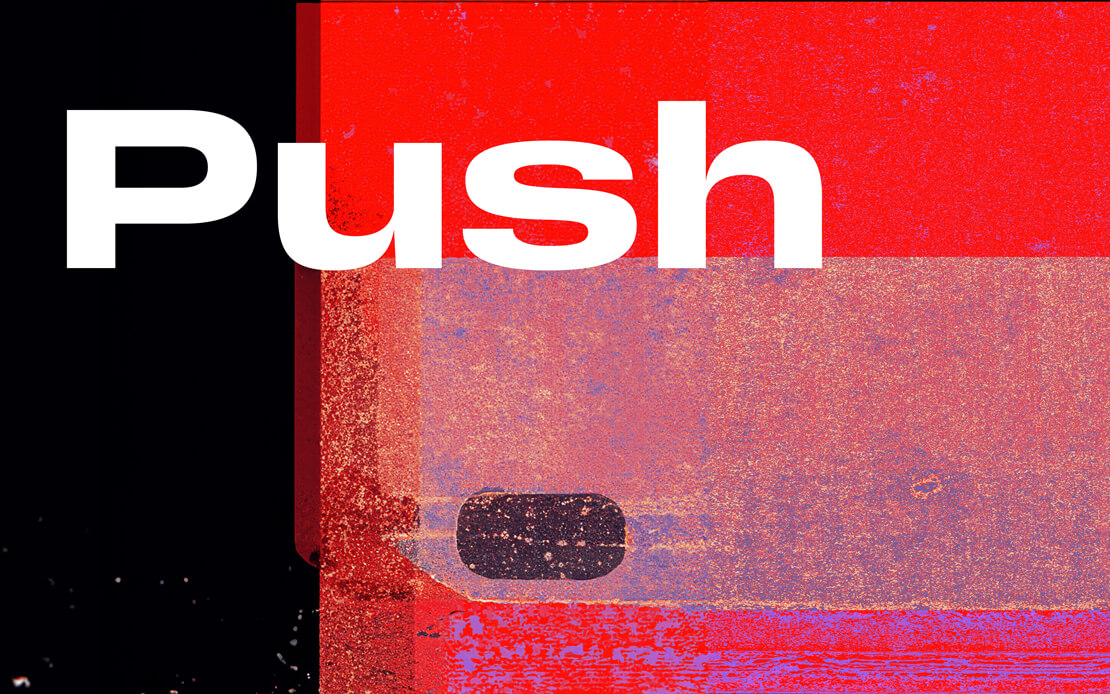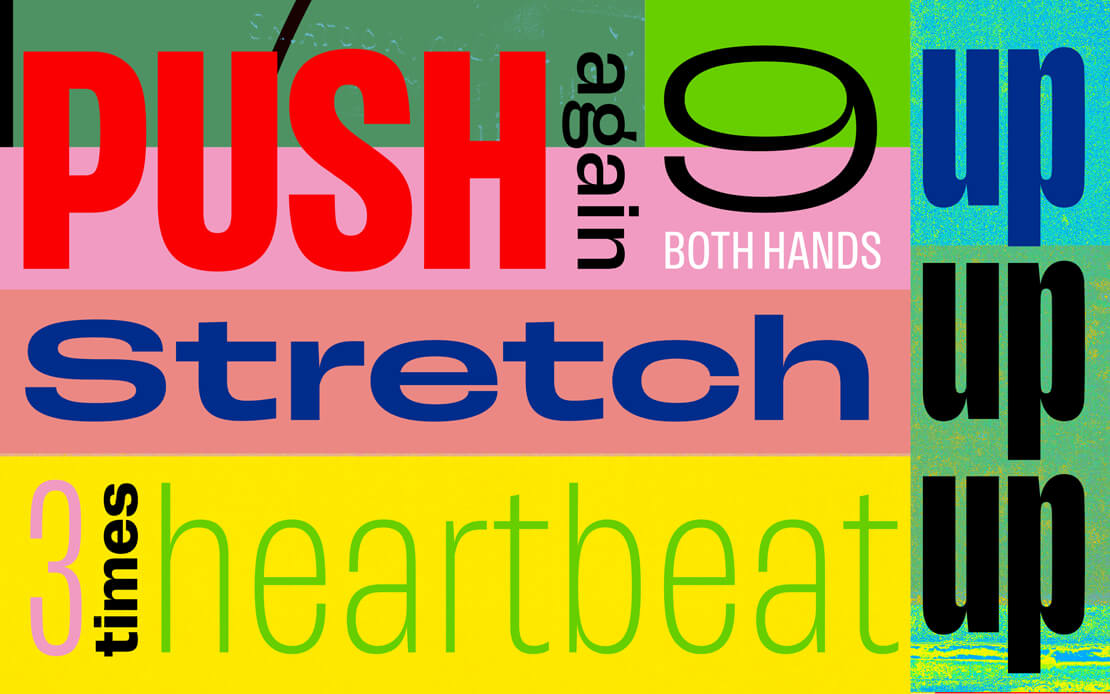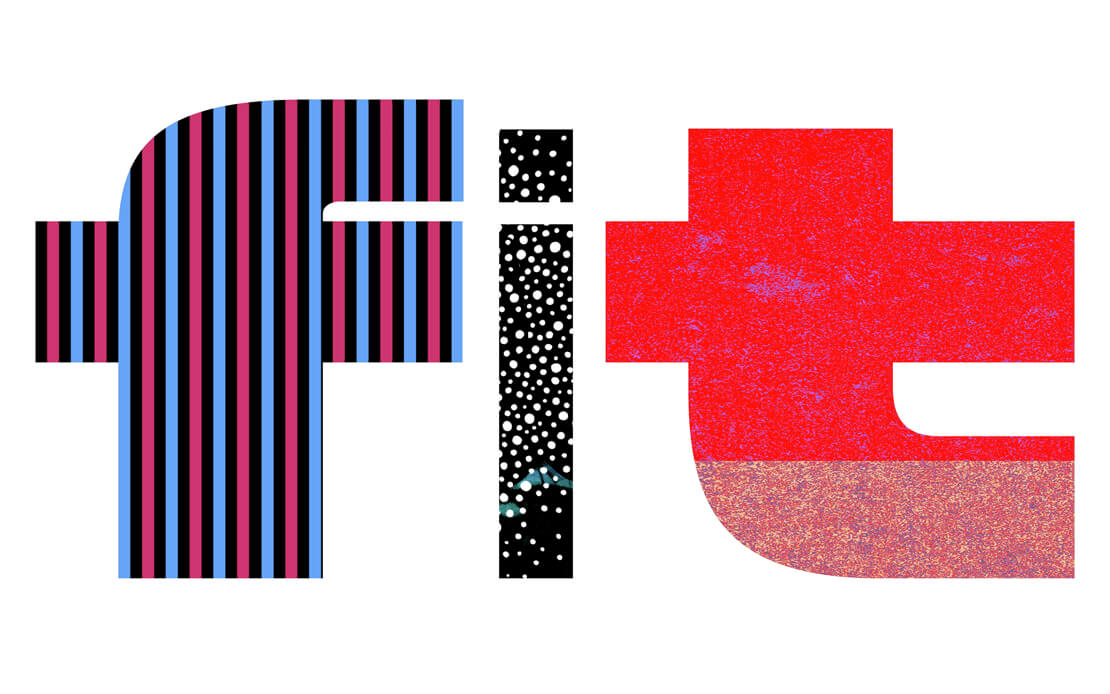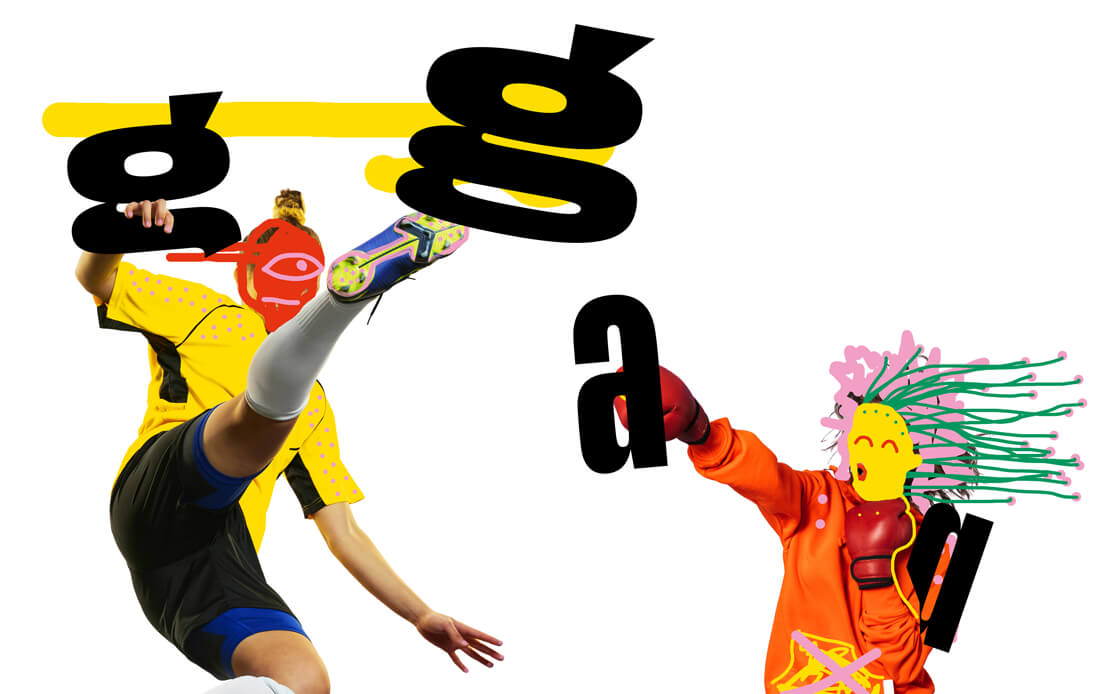
Neue Schriftfamilie »Push« bei Fontwerk erschienen
Fontwerk hat die von Christine Gertsch gestaltete Schriftfamilie »Push« veröffentlicht. Sie enthält sieben Weiten in acht Stärken und vereint dabei Eigenschaften aus amerikanischen Gothics und europäischen Grotesken.
Das Schriftbild von der Schriftfamilie Push bringt Elemente aus den ersten 100 Jahren der serifenlosen Schriften zusammen. Zum Beispiel ist das schmale, fette »G« ohne Querstrich von der Schrift »Seven-Line Grotesque« von Thorowgood aus den 1830ern inspiriert. Das kleine »a« hingegen erinnert an die »Plak« Schrift von 1930.
Push enthält auch eine besondere Auswahl an »g«-Buchstaben: ein anglo-amerikanisches »Brillen-g«, ein zweistöckiges »Grotesk-g« und ein dänisches »g« ohne Schlaufe. Somit kombiniert die Schrift Elemente aus der neuen und der alten Welt miteinander.
Anstatt die gesamte Schriftfamilie einer umfassenden Anpassung zu unterziehen, konzentrierte sich die Designerin Christine Gertsch zuerst auf die extremen Varianten der fetten Schrift. So konnte sie die Kurven besser steuern und musste keine großen Kompromisse eingehen.
Die gezielte Anpassung der Kurvenverläufe ist bei dieser Schrift ein wichtiges Merkmal, das in allen Varianten zu finden ist. Die Kurven reichen von fein und spannungsvoll in den sehr schmalen und leichten Ausführungen bis hin zu kräftig und selbstsicher in den breiten, schweren Schnitten. Die Standardvariante von Push hält sich in etwa zwischen diesen Extremen auf.